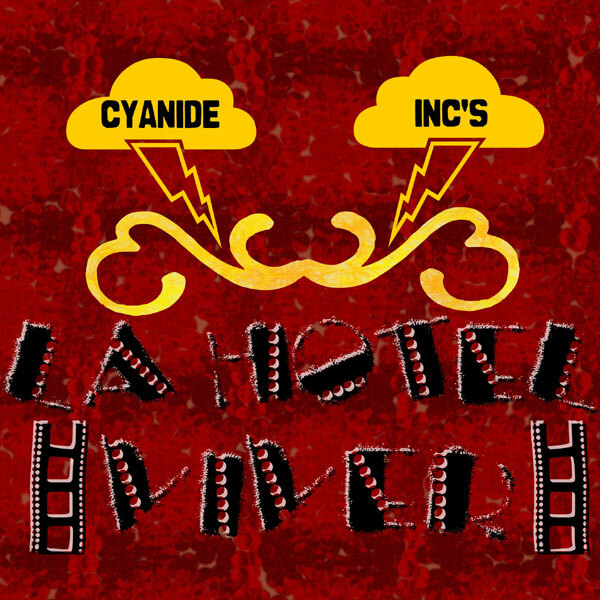
La Hotel Viver to darmowy, erodowany krój typu display o surowym, miejskim stylu, przypominającym podniszczone plakaty. Litery wyglądają na zakurzone, zadrapane i lekko niestabilne, a rząd okrągłych kropek powtarzający się w formach nadaje całości rytm hotelowego neonu.
To połączenie idealnie pasuje do ulotek klubowych, tytułów filmów niezależnych, opakowań płyt, brandingu butików i plakatów eventowych, gdzie potrzebny jest darmowy font z charakterem i wyrazistym, graficznym akcentem. Sprawdza się również w krótkich nagłówkach i na okładkach, ponieważ postrzępione krawędzie i kropkowane wypełnienia robią wrażenie jeszcze zanim zaczniemy czytać słowa.